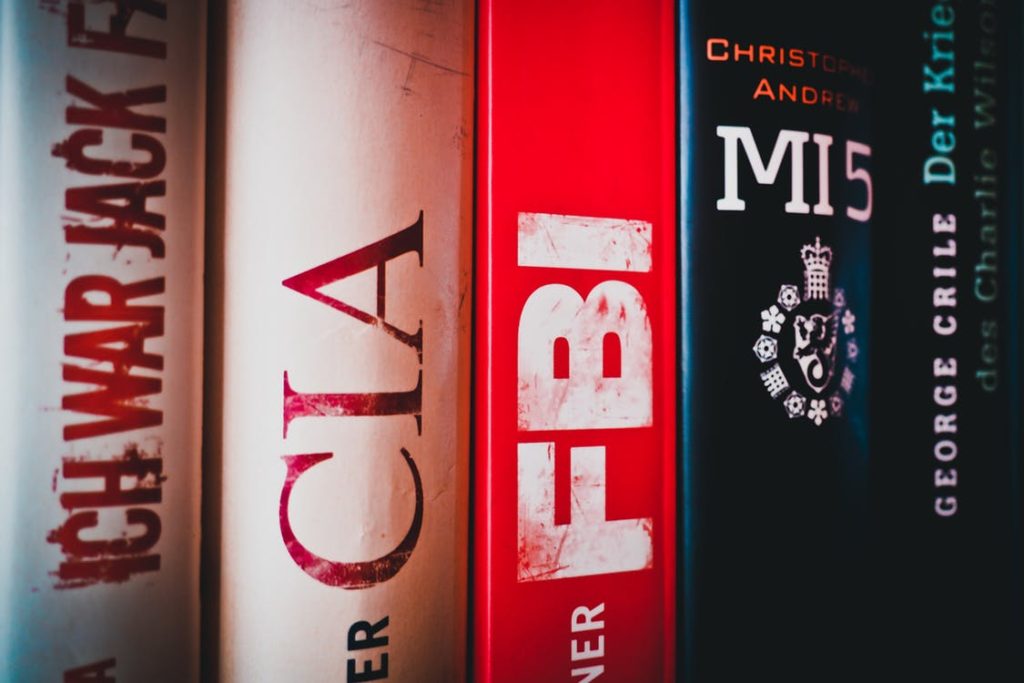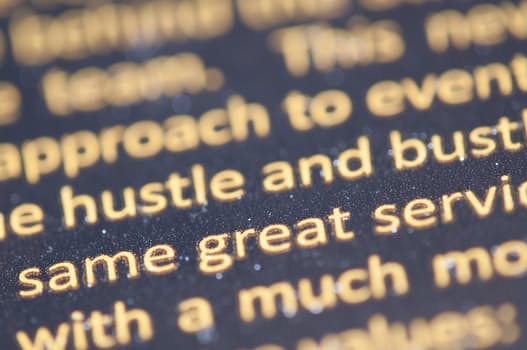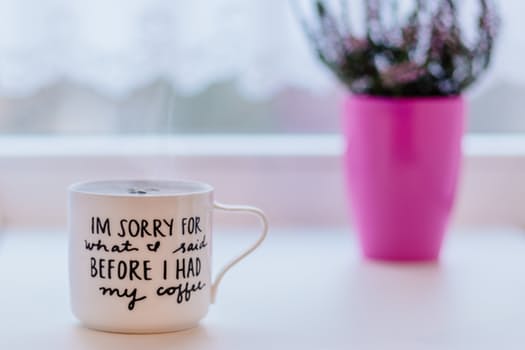
Někdo to vůbec neřešíte, někteří z vás to řeší až moc. A protože výběr fontu je můj denní šálek kávy, tak já vám tu alchymii trošku popíšu. Třeba potom pochopíte, proč zrovna já na vás odpověď na tuto otázku nevybafnu obratem.
Otázka č. 1: Pro jaký text font vybíráte?
Ano, tak jako máte kousky v šatníku, které si nevezmete do divadla, tak se i každý font hodí na něco jiného. Z praktického i psychologického hlediska.
FONT PROSTĚ MUSÍ PLNIT SVŮJ ÚČEL.
Tečka. Není tam na ozdobu, i když to tak někdy vypadá. A ten účel může být různý. Záleží na kategorii textu. Tady máte čtyři nejdůležitější kategorie:
#1 Nadpis
Účel: uvádí téma a přitahuje pozornost.
Zaujme, nebo nezaujme a čtenář mizí. Jeho hlavní úlohou je tedy přitáhnout pozornost čtenáře a zároveň rezonovat s tématem. Takže žádné malé mršky, ani stejný font jako zbytek textu. Font musí být dostatečně výrazný (druh, řez, velikost) a zároveň mít stejnou energii jako téma článku. Jiný font si vybere autor článku o nejnovějším modelu IPhone, jiný autorka článku o módě v Paříži.
Ale pozor, neznamená to, že musíte vybírat neobvyklé fonty, naopak. Energie fontu je v detailech, v tazích, patkách, křivkách. Heslo „čím výraznější, tím lepší“ tady v žádném případě neplatí.
#2 Podnadpis
Účel: rozvést a podpořit nadpis.
Musí jednoznačně ladit s nadpisem. Doplňovat jeho sdělení a stát trošku v pozadí. Kombinace fontů vydá na samostatný článek, brzy se ho dočkáte. Samostatnou kapitolou jsou mezery mezi nadpisem a podnadpisem a zbytkem textu. To byste nevěřili, jakou úlohu to prázdné místo může hrát. Ale tady není čas na mezery, jdeme zpátky k fontům.
#3 Odstavec
Účel: být lehce čitelný.
Dlouhý text, který se skládá z více vět. Tady platí jednoduché pravidlo – musí se dobře číst. Ne, že to musí jít jakž takž přečíst, ale musí být tak dobře čitelný, aby vám čtenář nevzal roha. Aby nemusel:
- Louskat malinkatá písmenka.
- Přemýšlet, jaké písmenko se za kudrlinkou skrývá.
- Unavovat oči příliš tenkým fontem.
Apod.
Ono co si budeme povídat, textů je všude okolo nás hodně a když se mi nějaký blbě čte, tak si vyberu jiný. Takže nejenom fonty zdobené a „speciální“ se nehodí, ale vyhněte se i fontům moc úzkým, moc širokým, příliš tenkým, příliš tlustým,… 🙂
Prostě si pamatujte, tady NEEXPERIMENTUJTE.
Když nevíte kudy kam, klasické Calibri to jistí.
#4 Osobní text
Účel: zapojit emoce.
Nadpis má vyjadřovat emoce tématu, osobní text má hodně společného s vámi. S vámi osobně. Na žádném jiném fontu se tolik neprojeví osobnost pisatele. A co to je za text?
- Věta, kterou popisujete váš záměr
- Někdy jím píšete vaše jméno
- Oblíbený citát
- Myšlenka, se kterou se ztotožníte
- Věta, kterou se popisujete
- logo
Prostě něco, co jde z hloubi vaší duše, máte k tomu vztah a někdy i váháte, jestli to publikovat.
Jste za tím vy a jenom vy a právě tím můžete oslovit to vaše publikum. A výběrem fontu zacílíte na to správné. Přitáhne lidi, kteří s vámi rezonují, naladí se na vás a budou vědět, co čekat. Nehrozí zklamání z nenaplněných očekávání.
Teď už vidím, jak některým z vás vstávají hrůzou vlasy na hlavě:
„mám problém vybrat jeden font, to mám vybírat tři?
Klid, nemusíte.
Ale pokud chcete vybrat font, který splní svůj účel – tj. pozvedne text o třídu výš, tak popřemýšlejte nad tím, pro jakou kategorii asi hledáte.
Otázka č.2 – Pro koho píšete? Při jaké příležitosti?
Často opakuji, že s fontem je to jako s oblečením. Ale když ono to tak opravdu je. Takže když mám vybrat font, potřebuji vědět, na co vy ho asi tak použijete, a hlavně pro koho – kdo bude čtenářem.
Nevíte? No tak počkejte, určitě víte, pro koho píšete články. Kdo chodí na váš web, nebo pro koho je text určený? A je jedno o jaký text se jedná, ať je to leták, prezentace, nebo kniha.
Když bych to měla přehnat – kudrlinkované písmo určitě nepoužijete pro IT příručku, že? A strohé, studené písmo se také nehodí do letáku pro nastávající maminky. To už je právě ta psychologie a řeč podvědomí. Divili byste se, co vše váš mozek stihne při čtení textu analyzovat.
Otázka č.3 – Jací jste vy?
Ale ano, je to tak. Každý má svůj nezaměnitelný rukopis, každý má svůj styl vyjadřování a každý z nás si vybírá písmo podle svého charakteru. Takže vám nebudu nutit nějaké, které se k vám vůbec nehodí, i kdyby se nastokrát hodilo k tématu.
Jste společenská, stojíte nohama na zemi a máte rychlé a logické myšlení?
Otázka č.4 – Kombinace fontů.
Ať vyberete sebelepší fonty, můžete je úplně zabít nevhodnou kombinací. Nejsem proti nezvyklým kombinacím, naopak, třeba tady si Michala Měřínská moc hezky pohrála s kontrastem tenkého úzkého patkového fontu a rozevlátého ručně psaného:
Zabijákem jsou spíš kombinace, kdy si jsou fonty podobné, ale ne úplně. Jsou přibližně stejně velké, ale působí nesourodě. Prostě místo, aby se podpořily, tak výsledek působí tak nějak… nemastně neslaně.
Zajimave cteni diky. Jeste byste mohla napsat o tom ze kdyz piseme cesky a font to nepodporuje je krajne hloupe takovy font pouzit. To me desne toci. žščřěň atd napsano v kroucenem fontu ktery tyto pisma neumi je desny.
Prosim jake jsou to fonty pouzite na
Dobrý den, ano, to je oblíbené faux-pas. Nedivím se, že vás to točí. 🙂
Fonty jsou: Shadows into Light a Just Me Again Down Here.